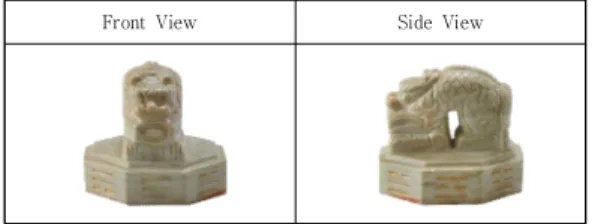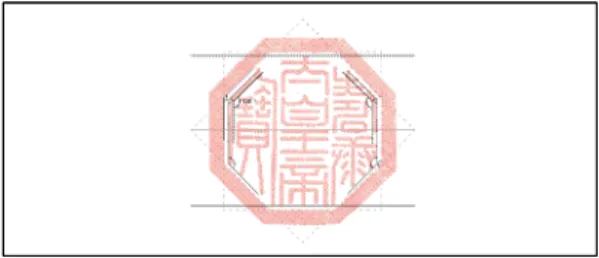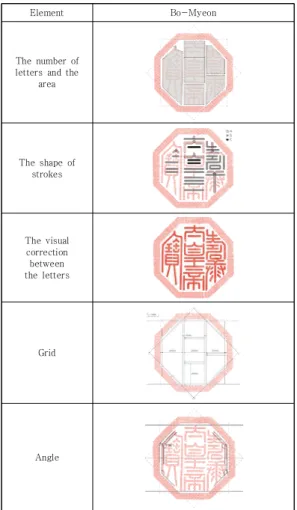
조선시대 어보 수강태황제보(壽康太皇帝寶) 서체 형태 연구
A Study on the Typeface of Font, the Shape Royal Seal of the ex-Emperor Sugang in the Joseon Dynasty
요 약 인장은 개인이나 집단을 증명하는 도구로써 한국을 포함한 주로 동양 문화권에서 많이 나타난다. 한국의 인장문 화에서는 국가를 상징하는 인장을 용도에 따라 국새와 어보로 분류한다. 국새와 어보는 서체를 사용하여 이름이나 직위 를 나타내며 그 서체는 인장마다 다르고 시대별로 다양하게 변화되어 왔다. 대한민국은 현재 사용하는 국새 이전의 모든 국새와 어보는 한자로 제작되었다. 본 논문은 어보를 통하여 타이포그래피의 구성요소를 분석하며 연구대상은 조선시대 의 여러 어보 중 유일하게 8각 보면 어보인 『수강태황제보』이다. 어보의 외형적 형태가 아닌 보면(寶面)에 나타난 보영 (寶影)은 각각 아름다운 서체와 비율로 예술적 가치를 갖고 있으며 이는 연구가치가 있다. 본 연구는 한국 인장의 특징에 대해 고증하고 『수강태황제보』의 보영 즉, 글씨를 타이포그래피 관점으로 구성요소에 따라 수치, 구조, 형태의 특징을 분석한다. 이를 통해 우리나라 역사 속 타이포그래피의 아름다운 조형미를 확인한다.
Abstract Seal is a tool to prove an individual or group. Guk-Sae and Eo-Bo uses typeface to represent their names or titles, which change from tensile to tensile and have varied from time to time. Although the Korean alphabet currently uses Hangul, it had used Chinese characters before Hun-Min-Jeong-Um was created in 1443. All seals and royal seal before the Korean Seal of State were made in Chinese characters. This thesis analyzes the concept of typography through the royal seal, and the subject of this study is ‘Sugang Emperor’ which is the only eight-letter version seal of the Joseon Dynasty's various royal seal. Bo-Yeong, which is shown in Bo-Myeon has artistic value with beautiful typeface and proportions, which is worth research. It examines the features of the Korean seal, analyzes and studies the typeface shape and features from the typographic perspective of the "Sugang Emperor Bo-Yeong,"
or writing.
1. 서론
1.1 연구의 배경과 목적
인장(印章)은 개인이나 집단을 증명하고 상징하는 도 구이다. 과거 조선시대 국가를 대표하는 인장으로는 크게 국새(國璽)와 어보(御寶)가 있다[1].
국새는 국가를 상징하며 왕위 계승 시 선양의 징표인 동시에 외교문서나 왕명 문서 등 실무적으로 사용하였다 [2]. 어보는 임금이나 왕비의 덕을 기린다 하여 올리던 칭 호인 존호, 제왕이나 재상
, 유현2)
들이 죽은 뒤에 그들 의 공덕을 칭송하여 붙인 이름인 시호, 황제나 왕이 죽은 뒤 종묘3)
에 신위를 모실 때 붙이는 호인 묘호4)
등이 올 려질 때 제작하여 사용했다[3].인장에 글자가 새겨진 면은 인면(印面), 어보에서는 보 면(寶面)이라 불린다. 보면은 주로 한자 서체인 전서로 쓰 이며 아름다운 서체와 비율로 예술적 가치를 갖지만 어 보의 형태에 비해 보면은 아직까지 연구 자료가 많지 않 다. 특히 각 어보별로 가장 큰 특징이라고 할 수 있는 보 면의 글씨는 타이포그래피 관점에서 연구 가치가 크다.
본 연구에서는 우리나라의 어보 중 하나인 『수강태황 제보』를 디자인에서 기초가 되는 타이포그래피 관점으로 고딕체의 형태를 분석하고 이를 통해 우리나라 인장이 가지고 있는 특징을 찾고 우리나라의 인장문화를 고증하 는 것에 목적이 있다.
1.2 연구의 방법과 범위
수강태황제보는 2014년 4월 25일 한미정상회담에서 반환된 9점의 인장 중 하나로써 1907년 순종황제가 퇴 위한 고종황제 '수강'이라는 존호를 올리면서 제작한 어 보이다. 현재는 국립고궁박물관에서 보관 중인 수강태황 제보는 조선시대 어보 366점 중 유래를 찾을 수 없는 유 일한 8각 형태로 역사적 가치가 크다[4].
본 연구에서는 수강태황제보 보면의 형태를 분석한다.
옥책
에 새긴 송덕문인 ‘옥책문’을 참고하여 보면의 서체1) 재상(宰相): 임금을 돕고 모든 관원을 지휘하고 감독하는 일을 맡아보던 이품 이상의 벼슬. 또는 그 벼슬에 있던 벼슬아치 2) 유현(儒賢): 유학에 정통하고 언행이 바른 사람 3) 종묘(宗廟): 조선 시대에, 역대 임금과 왕비의 위패를 모시던 왕
실의 사당
4) 묘호(廟號): 임금이 죽은 뒤에 생전의 공덕을 기리어 붙인 이름 5) 옥책(玉冊): 제왕이나 후비(后妃)의 존호를 올릴 때에 그 덕을
기리는 글을 새긴 옥 조각을 엮어서 만든 책
를 박물관자료를 참고로 하여 진행한다[5](Fig. 1 참고).
Fig. 1. The Collection of texts in the Jade Book for the Bestowal of Honorific Title upon Emperor Gojong
2. 본론
2.1 어보의 역사적 고찰 2.1.1 인장문화의 흐름
인장의 기원은 주로 현전하는 유물 가운데 가장 이른 시기의 사례를 통해 추측하고 있으며, 대략 기원전 3,500년 전으로 알려져 있다. 인장문화를 미술의 한 장 르인 전각예술로 계승한 나라는 중국, 한국, 일본 등에 불 과하다. 한국 국새에 관한 기록은 증보문헌비고에 부여 예왕의 국새인 ‘예왕지인(濊王之印)’에 관한 기록이 가장 오래되었다. 또한 고구려시대는 『삼국사기』, 고려시대는
『고려사』의 ‘인장’조, 조선시대는『증보문헌비고』의 ‘새인’
조에서 국새에 관한 기록을 찾을 수 있다[6]. 조선시대 헌 종은 궁궐에 국내외의 인보를 수집하여 <보소당인존>을 편찬하기도 하였고, 고종은 화재로 인해 많은 인장들이 망실되자 다시 복각하여 보장했다. 이러한 사실들은 조선 왕실이 인장 문화를 얼마나 중시하였는지 알 수 있다[7].
현재 대한민국 국새의 인문은 대한민국을 한글로 가로 새기며 훈민정음 창제 당시의 자체를 사용한다.
2.1.2 어보의 의미
한국의 인장은 고대, 중세의 자료가 부족하여 온전한 분류가 어려우므로 현재로선 조선시대를 중심으로 할 수 밖에 없다. ‘국새’, ‘옥새’는 ‘어보’에 비해 비교적 익숙한 단어들이다. 그러나 이 단어들의 차이는 불명확하다. 많은 자료에는 국새는 ‘국가의 상징이자 국가적 문서에 사용되 는 국가의 인장’으로 국왕의 각종 행사 시 위엄을 나타내 기 위해 행렬의 앞에서 봉송하기도 했다. 옥새는 ‘옥으로 만든 국새’ 혹은 ‘황제가 사용하는 인장’으로 알려져 있다.
조선왕실의 어보는 ‘왕실의 권위를 상징하는 의례용
인장’으로 왕비와 왕세자, 왕세손과 그 빈들의 책봉 때에 제작(책봉보인)하기도 하고 왕실의 선조에게 존호를 올 릴 때 제작(존호보)되기도 한다. 또한 사후에 시호를 올 릴 때(시호보), 국왕이 승하하였을 때(묘호보) 등이 있다 [8]. 왕실인사의 책봉 때에 제작된 인장은 국왕과 왕비 외 에는 모두 ‘인’자를 써서 ‘보’와 구별하였고, 존호와 시호, 휘호와 관련한 인장은 ‘보’로 한 점이 특징이다. 이는 왕조 의 영속성과 왕실의 정통성을 상징한다. 이 밖에도 조선왕 실의 인장에는 개인적 용도로 사용하던 사인 등이 있다[9].
2.1.3 어보의 서체와 상징
인장에 글자가 새겨진 면은 인면이라 불리며 어보에서 는 보면이라 불린다[10]. 보면은 아름다운 서체와 비율로 예술적 가치를 갖는다. 인장을 새기는 행위, 또는 새겨진 인장을 ‘전각
6)
’이라 하듯이 여기에 쓰이는 서체는 전서가 주종을 이루고 있다. 조선시대 어보에 사용한 서체는 대 부분 구첩전(첩전, 혹은 상방대전)이며 인전의 한 형태로 필획을 중첩하고 쌓아 올려 인면을 가득 메우는 서체이 다. 필획이 많이 중첩된 경우 10첩 이상인 경우도 있다.첩전은 어보와 관인에 사용한 특별한 서체로서의 의미도 있지만, 위조를 방지하기 위해 발생하였다. 조선시대 전 기간에 걸쳐 사용하였던 Fig. 2의 상방대전(구첩전 혹은 첩전)은 대한제국기로 넘어오면서 큰 변화를 보이며 대부 분 간명한 ‘소전’으로 바꾸었다. 소전은 전서의 일종으로 발생국의 명칭을 따 진전이라고도 하며 대전과는 상대 개 념이다. 진시황이 천하를 통일하고 승상 이사로 하여금 만 들게 하였다고 전한다. 소전은 이전의 문자에 비해 균일하 며 좌우 대칭의 정제된 형태로 나타나 제왕의 냉엄한 권위 를 상징한다. 대한제국은 조선왕조 500년 동안 사용하여 온 구첩전에서 탈피하여 황제국으로서의 위상을 소전에 담아 어보의 서체에도 반영하였던 것으로 여겨진다[11].
Gu-Chub-Jeon So-Jeon
Fig. 2. Gu-Chub-Jeon and So-Jeon
2.2 타이포그래피의 이해 2.2.1 타이포그래피의 정의
인류 탄생 이후 말을 기호 체계로 만들어 모래, 나뭇 잎, 돌, 종이에 새기게 된 문자는 현재까지도 소통의 도구로 사라지지 않고 있다. 뿐만 아니라 주변을 둘러보았을 때 글자 가 없는 곳을 찾기 힘들다 해도 과언이 아니다. 역사적으로 타이포그래피(Typography)는 활자로 디자인하는 과정과 그 결과였는데, 매체의 변화에 따라 그 영역이 점차 넓어졌다.